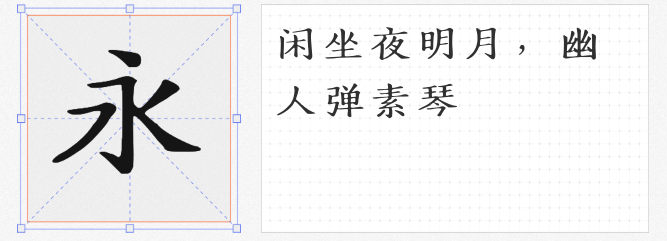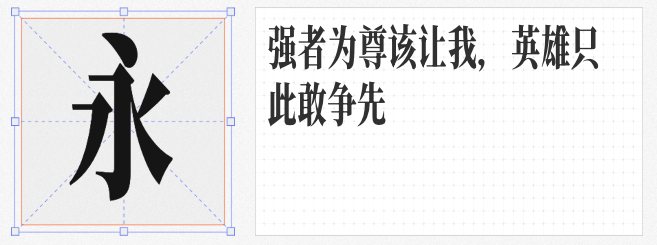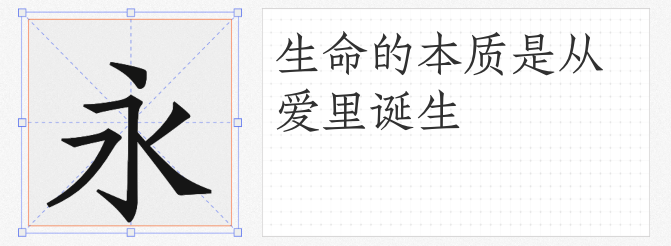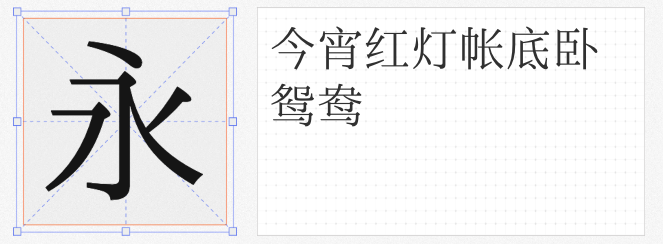
在商业设计领域,优质且可免费商用的字体如同宝藏,既能降低创作成本,又能以独特字形提升作品质感。以下四款字体以经典设计为基底,兼顾实用性与艺术性,助力设计师轻松打造专业级视觉方案。
由抖音设计博主猴尊开发的这款字体,以思源宋体为蓝本,将字形比例优化为黄金分割值,专为短视频竖屏阅读而生。其核心优势在于“缩行显字”——通过压缩字身宽度、拉长笔画韵律,单行可容纳更多字符且保持清晰度,适配手机端标题、短视频封面等场景。设计上,字体保留原笔画可编辑性(转曲线后仍可二次创作),并融入书法飞白笔触,在横竖撇捺的转折处透出灵动呼吸感,兼顾现代几何秩序与传统文人气质,为标题设计注入高级感。
专为长文阅读设计的润植家如印奏章楷,以传统小楷为灵感,字形方正中见骨力,结构疏密有致,横竖排皆显端庄。其笔画粗细均匀、起收笔自然,既无过度装饰的浮躁,亦无机械排版的呆板,尤其适合政府公文、古籍扫描排版、学术期刊等需要权威性与可读性的场景。竖排时如碑刻拓片般古朴典雅,横排时似信笺墨迹般温润自然,是打造“文化厚重感”的秘密武器。
以民国仿宋活字「南宋」为母版,朱雀仿宋在保留传统仿宋体“横细竖粗、点如瓜子、捺如扫帚”特征的基础上,优化了字符间距与字重分配,更适配现代屏幕阅读。其笔画转折处保留毛笔书写时的顿挫感,数字与拉丁字母设计亦延续中式美学,整体如一卷泛黄书页,适配文化类海报、复古包装、诗歌集等需要营造“时光沉淀感”的场景,为现代设计注入一缕民国文人的风骨。
基于日本开源字体「IPAmj明朝」改造的霞鹜新致宋,堪称中日字形规范的“翻译官”。设计师将原字库中不符合大陆规范的笔画(如“口”字右竖出锋、“木”字捺画弧度)逐一修正,同时保留其温润如玉的笔触与疏密有度的结构。这款字体既有日式宋体的典雅细腻,又符合中文排版习惯,适配小说正文、杂志内页、品牌文案等需要“温柔叙事”的场景,让文字如流水般自然流淌。
四款字体,或以黄金比例重构传统,或以书卷气浸润长文,或以民国风骨唤醒记忆,或以中日融合突破边界。它们不仅是免费商用的选择,更是设计师探索字形美学的灵感起点——以经典为基,让创意自由生长。